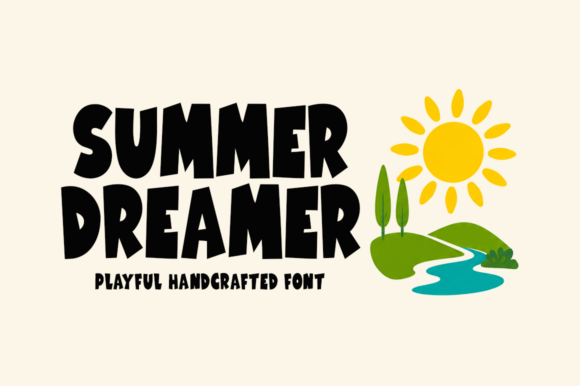
Summer Dreamer
Summer Dreamerのような高品質の素材をお探しの場合、このプレミアムパッケージはクリエイティブなプロジェクトに素晴らしい選択です。
POD(オンデマンド印刷)製品、結婚式の招待状、またはソーシャルメディアのグラフィックを作成している場合でも、Summer Dreamerは理想的です。